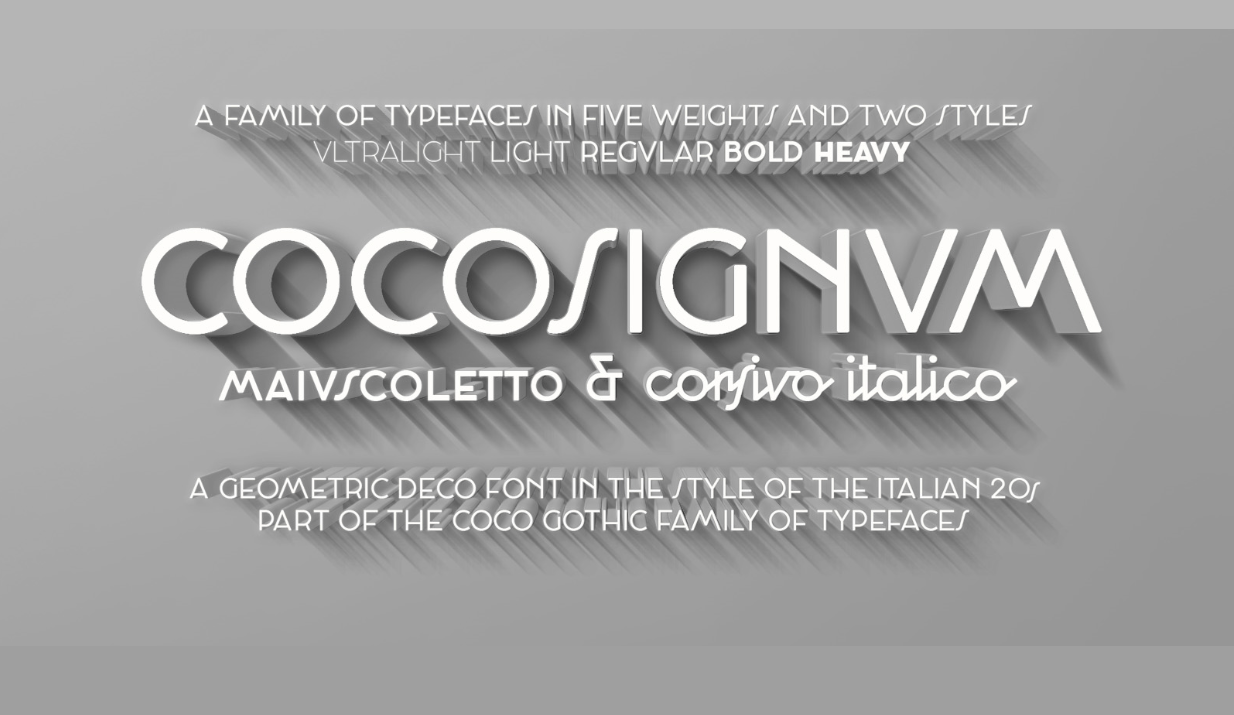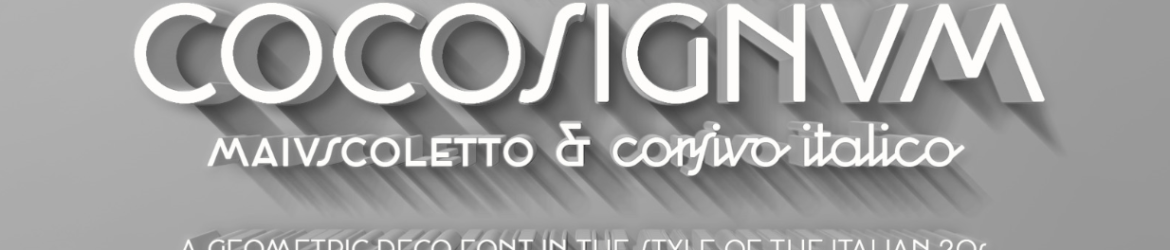
Na Cocosignum Font Family, a zetafonts oferece uma experiência visual única inspirada no fascinante mundo das tipografias dos anos 30 do sul da Itália. Inspirado por essa época marcante da história da moda e da cultura, o Cocosignum apresenta um estilo de letra imperativo com contornos decoraísticos propagandistas que ganham vida através de uma escrita geométrica e cursive na versão Corsivo Italico. Este conjunto de fontes vem em dois estilos e cinco pesos, abrangendo mais de quarenta idiomas usando o alfabeto latino, assim como grego e cirílico. Como uma seleção completa e avançada para designers e criadores de conteúdo, a Cocosignum é perfeita tanto para aplicativos digitais quanto para criações impressas, oferecendo um toque único e distintivo à sua marca ou produto.